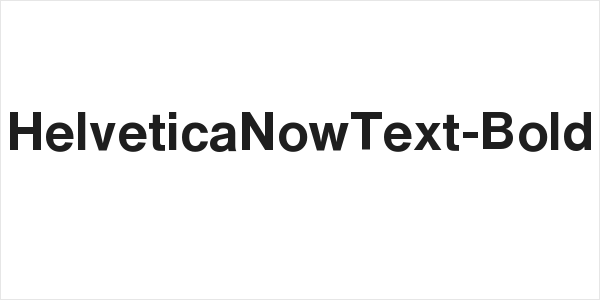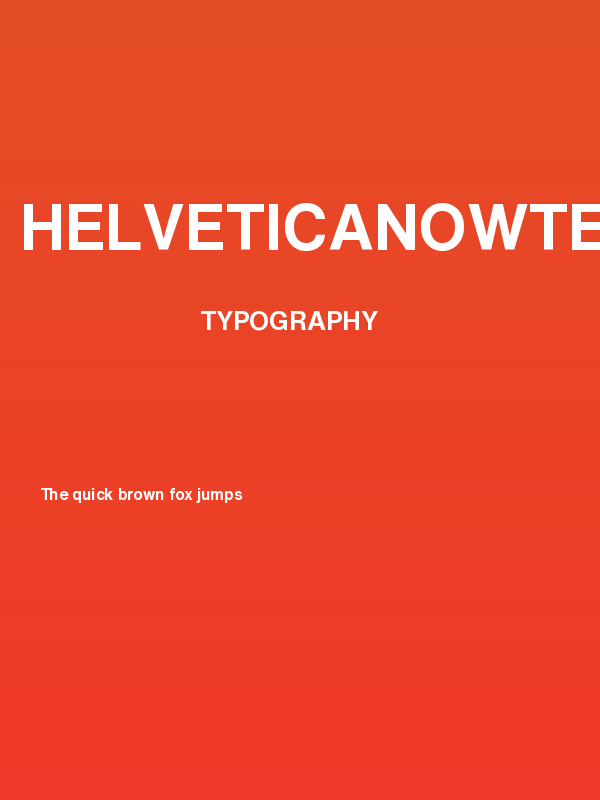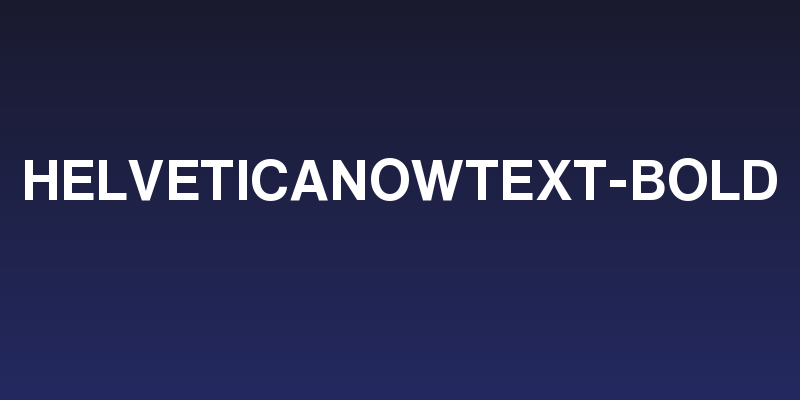
HelveticaNowText-Bold Font
✎ Sans Serif
| Anwendungsfall | Headlines, Body text, Logos |
| Vorgeschlagene Projekte | Ideal for branding, advertising, web design, and editorial layouts where clarity and modernity are key. |